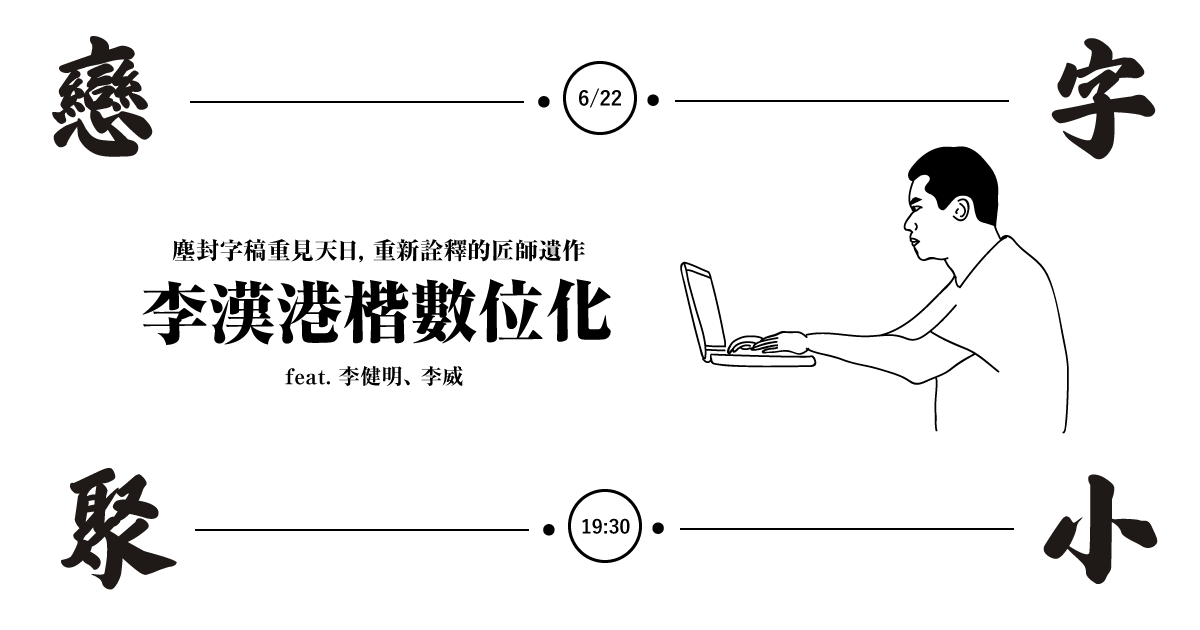
李漢是香港的「寫字佬」,即「寫招牌字的師傅」。與「招牌佬」李威為故友,兩人合作數十餘年,為香港的文字風景帶來經典的印記。
1992 年,李漢退休後,怕再也沒有人為老友寫字,便花費一年半載,寫成一本 5000 字的楷書字帖,與一本隸書字帖,特地從廣州送來香港給李威後,便離去了,連茶都沒喝到。
沒想到李威再次聽到好友的消息,竟是他的死訊。又當時因為電腦字型漸成為主流,再也不需用到這樣的字帖,這份作品便一直塵封著。
直到最近,李家父子才重新發現這款字帖的價值,試著探索使它重見天日的方式⋯⋯
我們特地趁著李健明、李威父子來台灣的機會,邀請他們到字戀小聚與我們分享這套字的前世今生,與他們讓李漢港楷重新問世的計畫。
李健明,1973年香港出生,李漢港楷數位化工作負責人。在學時一有休假便會在父親公司幫忙。96年大學畢業之後就全職投入公司工作,除了平時的手作程序外,還負責將部分工序機械化。
李威,李健明之父,李漢先生好友。生於1934年,50年代來港,曾從事電工,霓虹及招牌行業,於70年代認識街頭手寫字的李漢先生,漸成好友。現時仍未退休。